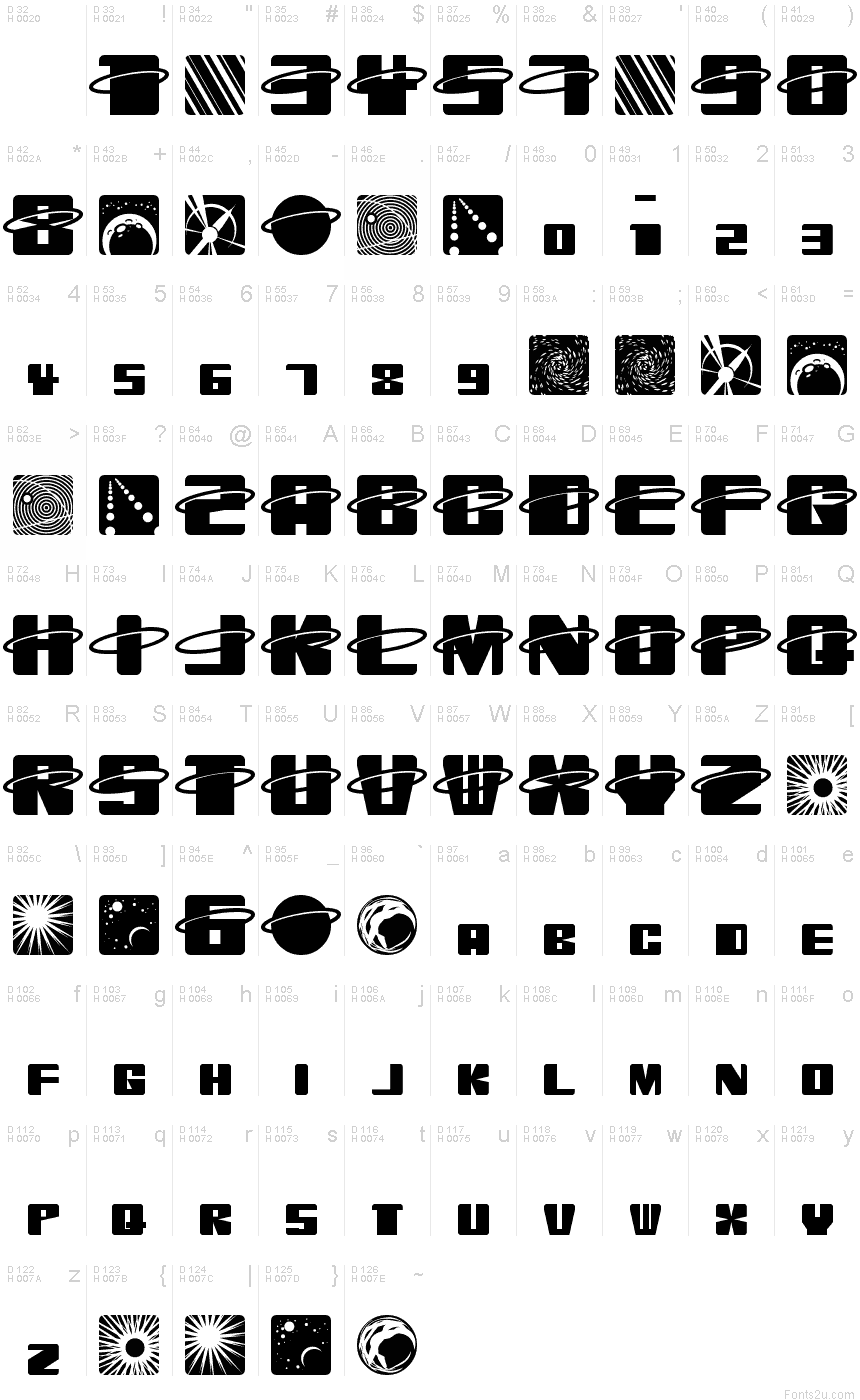
Orbitronio ist eine kostenlose Display-Schriftart im Space-Age-Look mit massiven, kräftigen Buchstaben und einer Prise Cartoon-Sci-Fi. Die Schrift wirkt wie aus abgerundeten Blöcken und scharfen Einschnitten zusammengesetzt; die ringförmigen Öffnungen verleihen dem Design einen retro-futuristischen Touch, perfekt für Logos, Arcade-Titel und Pulp-Sci-Fi-Grafiken.
Diese kostenlose Schrift ist ideal, wenn Sie eine spielerische, kosmische Note suchen: für Poster, Game-Branding, wissenschaftliche Kinderbücher, Event-Flyer, Sticker oder Titelkarten. Sie eignet sich hervorragend für kurze Schlagzeilen und Monogramme, da die Buchstaben groß, kompakt und voller silhouette-betonter Details sind, die den Stil sofort transportieren.